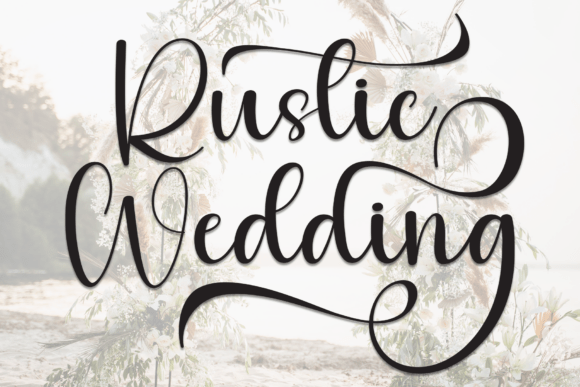
Rustic Wedding
หากคุณกำลังมองหาเนื้อหาคุณภาพสูงเช่น Rustic Wedding แพ็คเกจพรีเมียมนี้เป็นตัวเลือกที่ยอดเยี่ยมสำหรับโปรเจ็กต์สร้างสรรค์ของคุณ
ไม่ว่าคุณจะสร้างผลิตภัณฑ์ POD (Print on Demand) คำเชิญงานแต่งงาน หรือกราฟิกโซเชียลมีเดีย Rustic Wedding ก็เหมาะสมอย่างยิ่ง